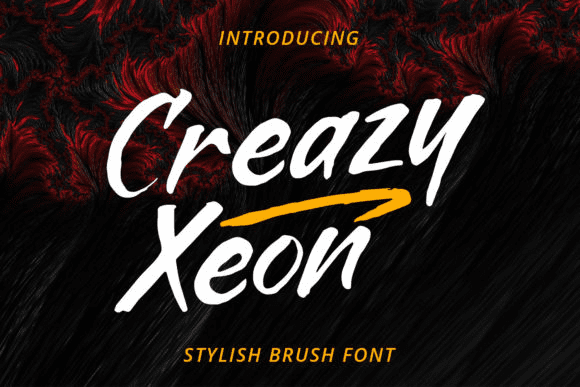
Название: Crazy Xeon Font
Crazy Xeon - стильный граффити-шрифт, вдохновленный уличным искусством.
Независимо от темы, этот шрифт будет невероятно полезен в вашей библиотеке шрифтов, поскольку он способен возвысить любое творение.